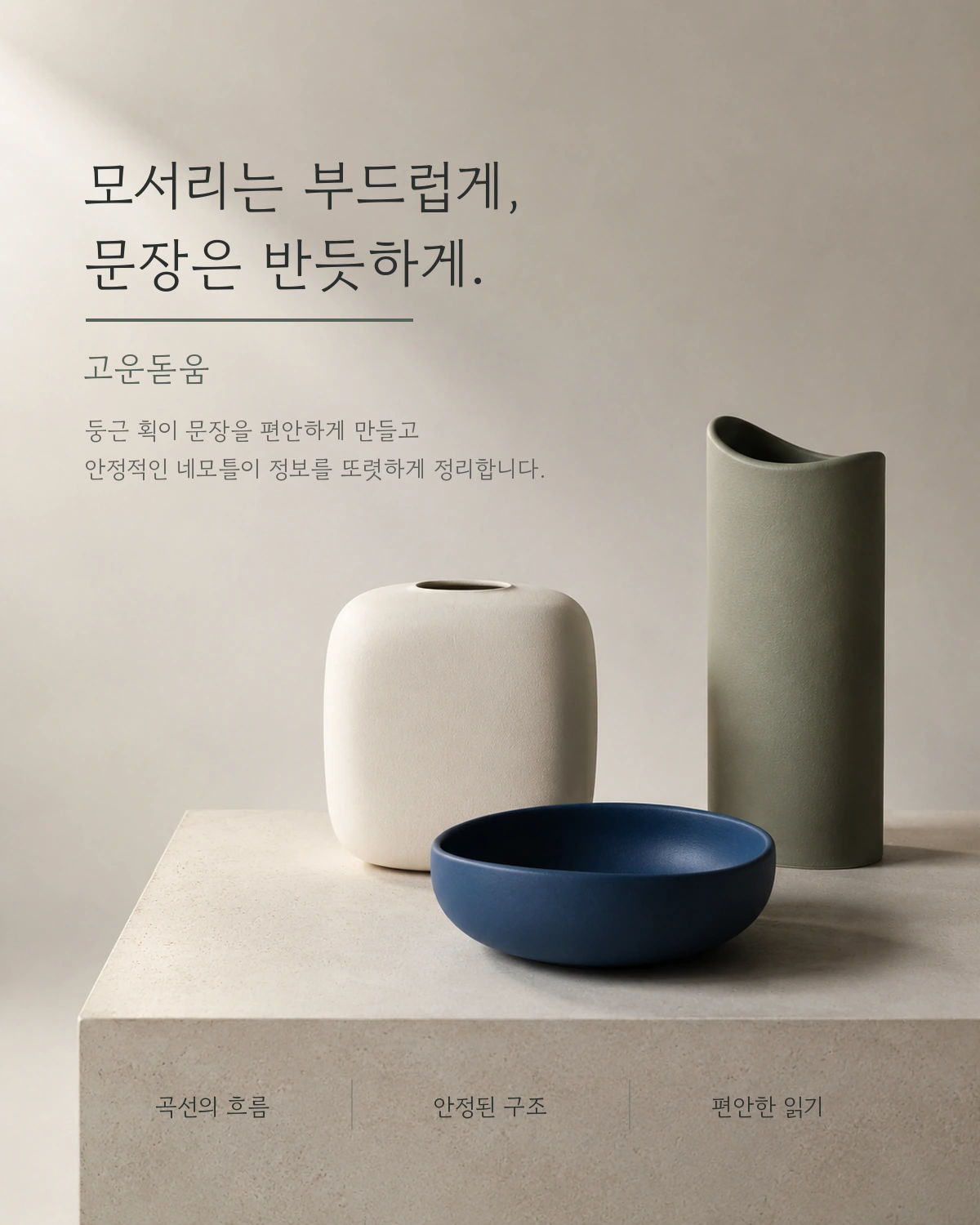
고운돋움 — 류양희에서 배포하는 무료 폰트입니다. 부드러운 곡선과 안정적인 네모틀을 바탕으로 단정하게 다듬은 고딕체
글꼴 디자이너 류양희가 만든 민부리 서체입니다. 아리따 부리를 그린 그 디자이너입니다.
출발점은 2010년으로 거슬러 올라갑니다. 한글글꼴창작지원사업의 지원을 받아 발표한 고운한글이 데뷔작이었고, 처음에는 바탕체만 계획했다가 돋움까지 더해 한 가족으로 넓혔습니다. 그리고 2021년에 완성형 11,172자로 확장하고 영문과 숫자를 새로 그려 구글폰트에 오픈소스로 공개한 것이 지금의 판입니다.
제작자가 밝힌 모티브는 연필로 쓴 손글씨 정체의 표정입니다. 구글폰트 소개는 이 서체를 손의 움직임이 살짝 배어 있는 휴머니스트 산세리프라고 설명합니다. 부드러운 톤의 본문이나 캡션, 카드 UI에 어울립니다. 다만 굵기가 Regular 하나뿐이라 강조를 굵기로 줄 수 없다는 점이 가장 큰 제약입니다. 위계가 필요하면 크기나 색으로 만들거나 짝인 고운바탕과 함께 써야 합니다.